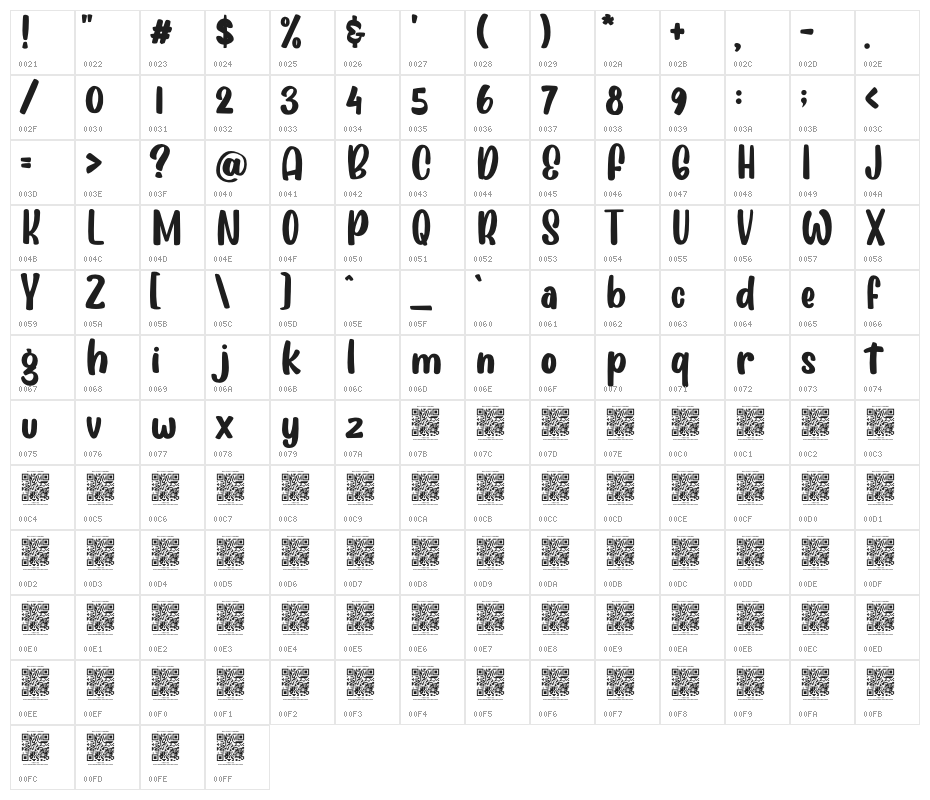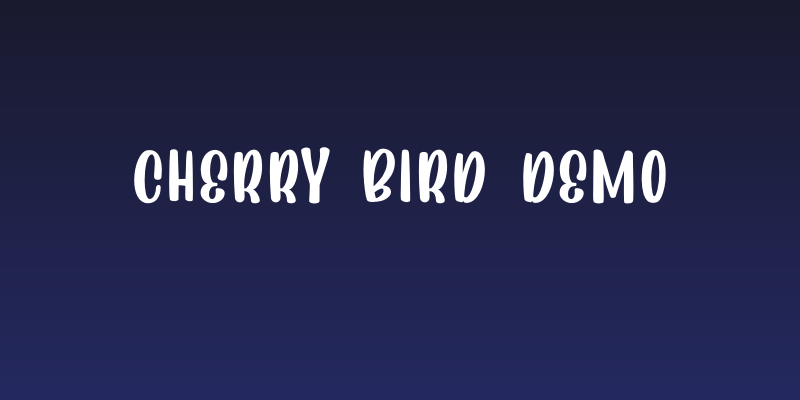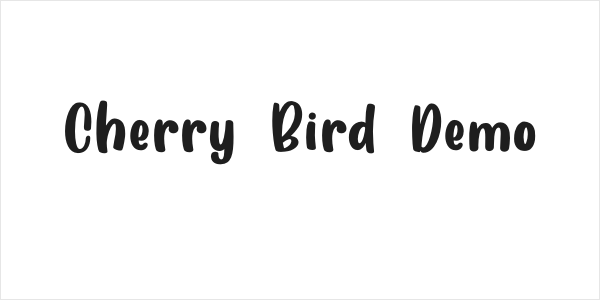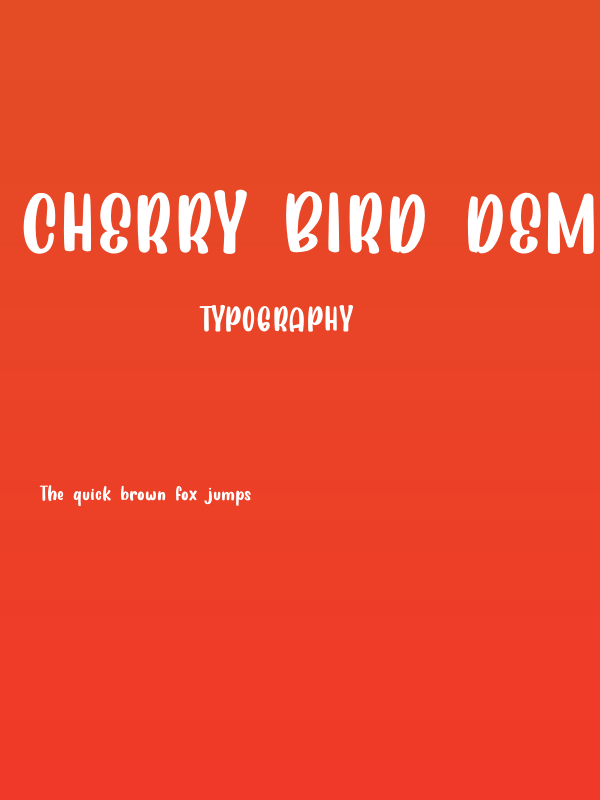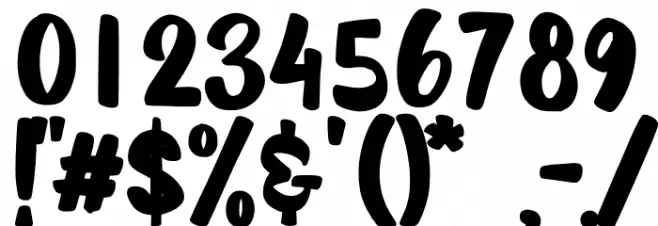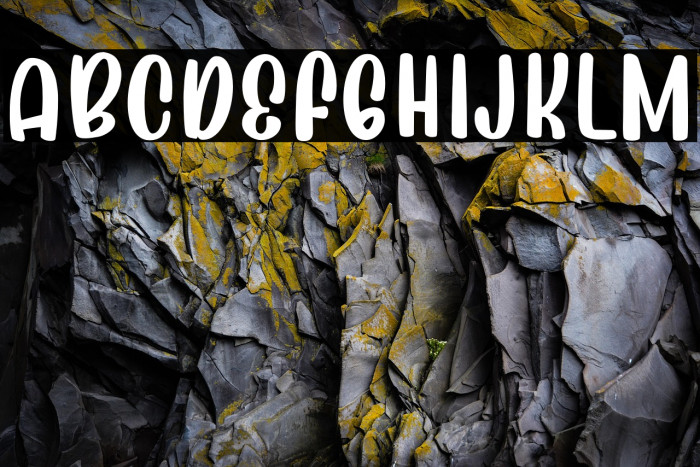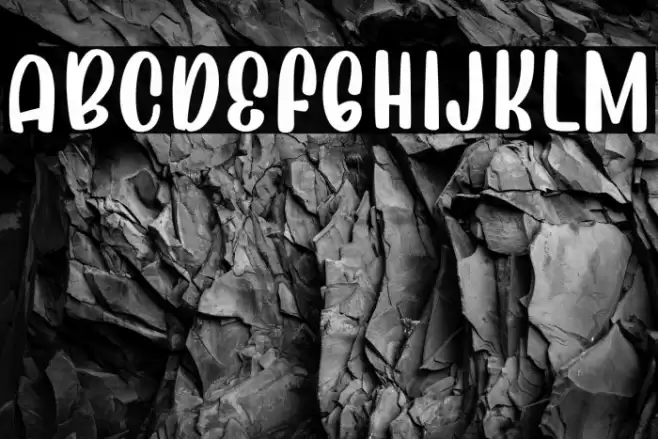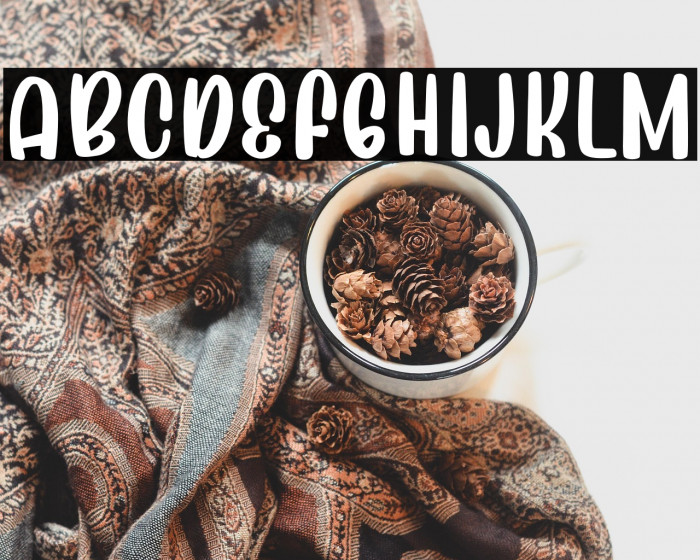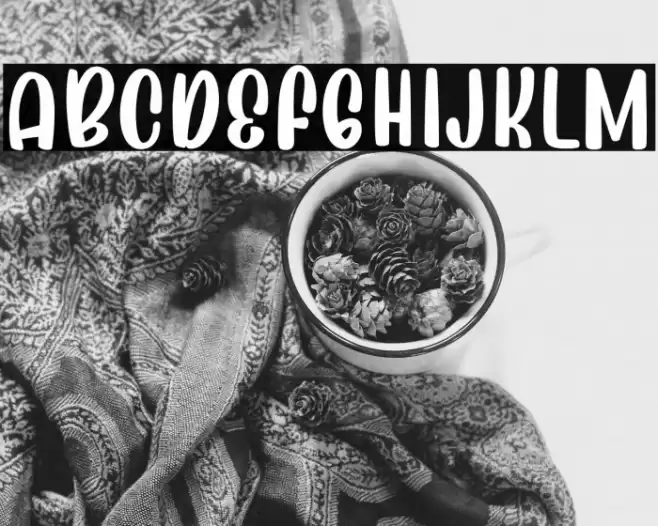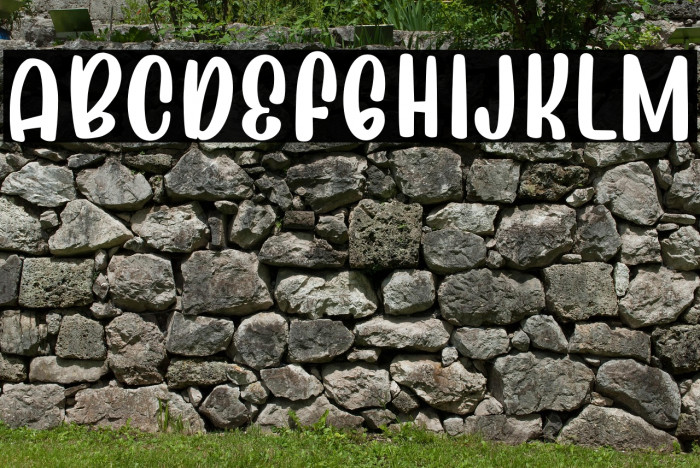
Cherry Bird Demo Font
CHERRY-BIRD-DEMO 大文字
CHERRY-BIRD-DEMO 小文字
CHERRY-BIRD-DEMO その他の文字
| おすすめプロジェクト | Ideal for children's books, playful branding, greeting cards, and creative posters. |